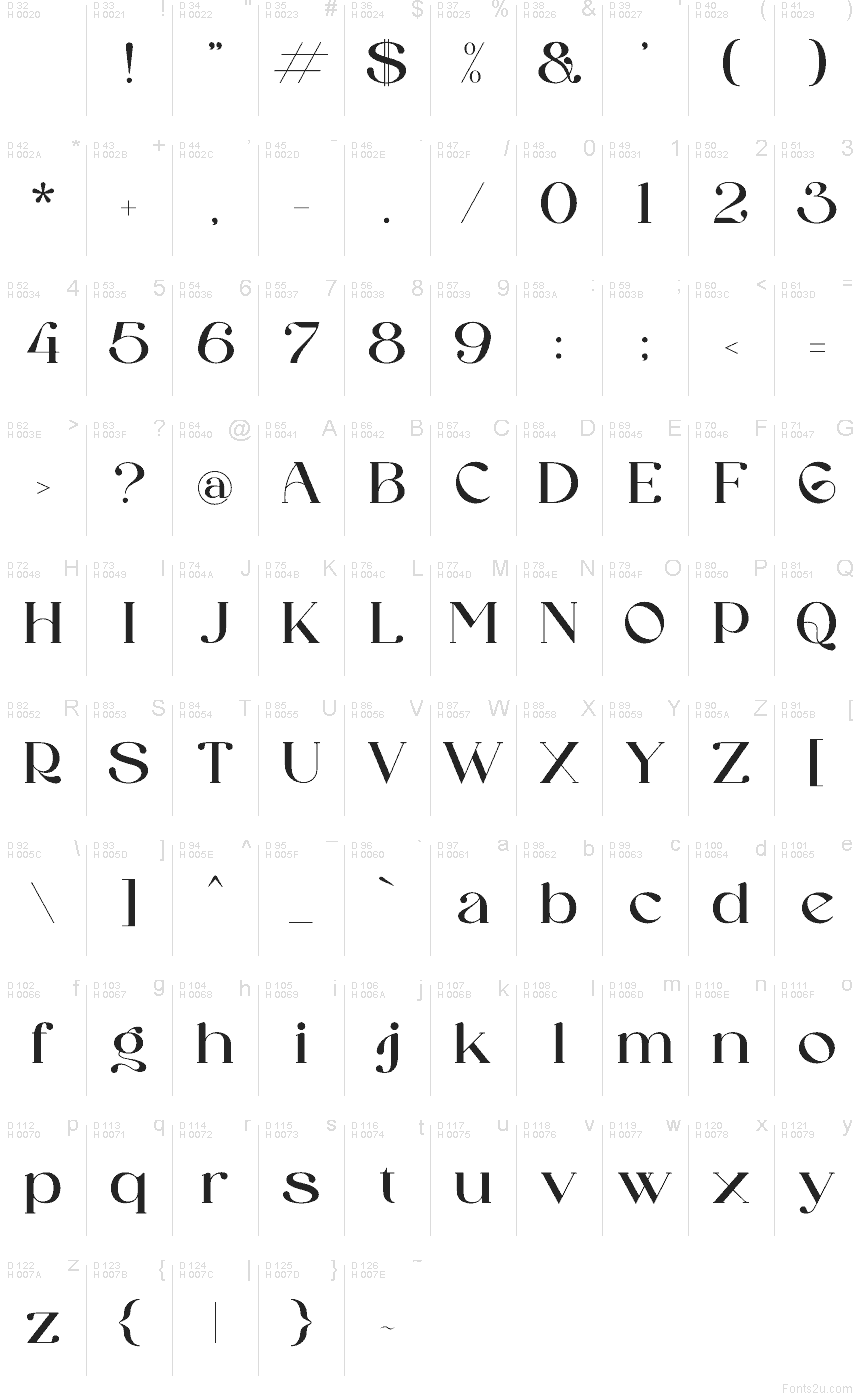
Galeriya, creata da Dede Nugraha di Gracetype Studios, è un font serif moderno e gratuito che unisce tratti sottili e affilati a curve eleganti e decise. I suoi contorni scolpiti e le forme quasi teatrali le conferiscono un'eleganza da galleria d'arte: raffinata, ma mai rigida. È leggibile e pulita, lasciando al contempo un segno grafico memorabile.
Con Galeriya otterrai risultati straordinari su copertine di libri, lookbook di moda, packaging di prodotti beauty, poster d'arte, branding per boutique, copertine di album e citazioni editoriali. Usala in dimensioni più grandi con un tracking generoso per far respirare i dettagli sinuosi e abbinala a un sans serif discreto per il testo principale: questo font gratuito ama i partner dallo stile sobrio.